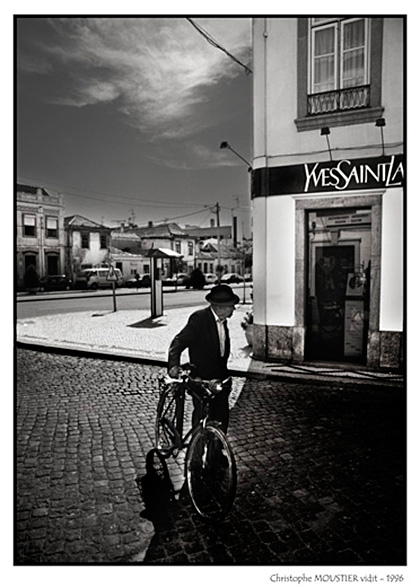
Yves Saint Laurent | la Transgression comme éthique de La Création
Logotype d’Yves Saint Laurent conçu par A.M. Cassandre. Évocation d’élégance, de créativité, de féminité; inclassable…C’est la grande patte d’un artiste complet, déjà «designer» dira Michel Disles.
Biographie d’Yves Saint Laurent
Yves Henri Donat Mathieu-Saint Laurent est né le 1er août 1936 à Oran en Algérie où il passe sa jeunesse.
En 1954, à l’âge de 18 ans, il s’installe à Paris où il suit des cours de dessin à la chambre syndicale de la haute couture pendant trois mois.
Maison Christian Dior
Christian Dior, le couturier qui a inventé le NewLook en raccourcissant les jupes des femmes d’environ 20-25cm (1945-1947)
Yves Saint Laurent est remarqué en 1955 par le couturier Christian Dior qui l’emploie comme assistant modéliste.En 1957, il est âgé de 21 ans à peine lorsque Christian Dior meurt. Il lui succède à la tête de la maison Dior où il connaît le succès avec la présentation de sa première collection  » Trapèze « . L’homme d’affaires Pierre Bergé entreprend de gérer sa carrière à partir de 1958 mais est mobilisé sous les drapeaux. À son retour, Marc Bohan a pris sa place auprès de son ami.
Vintage Fashion Newreels 1960s
Yves Saint Laurent, 1962
Yves Saint Laurent: ELLE magazine
Yves Saint Laurent, tout terriblement
L’œuvre d’Yves Saint Laurent a aussi bien sa place sur les corps au plastique parfait des femmes que dans le musée de la Mode, alors pourquoi pas sur le blog d’un graphic-designer qui pense que la création est forcément transversale et touche à tous les domaines. Je ne me suis pas privé d’évoquer le travail de Serge Lutens ou d’analyser la mise en page des magazines de Mode. Alors pourquoi devrais-je considérer qu’en la matière l’œuvre d’Yves Saint Laurent échapperait aux champs d’investigations de Design et Typo. (1) (2) (3)
Depuis la fin de la deuxième guerre mondiale les créateurs de mode se sont ouvert au monde du graphic design. Preuve en est aussi bien chez Christian Dior que Givenchy ou Ted Lapidus ou encore et bien évidemment Kenzo et Jean-Paul Gaultier sans oublier un des plus passionnés de graphisme Paul Smith. Il suffit de feuilleter les magazines sur le site de l’Officiel, pour s’en convaincre. Lignes parallèles ou croisés, trame à points façon Roy Lichtenstein. Le graphisme du Bauhaus, mais aussi la peinture cubiste de Picasso ou encore l’architecture de l’espagnol manière Gaudi ont pesé lourd sur les épaules frêles des manequins défilant d’un pas incertain sur les podiums des avant-premières.
Parce que la force créatrice des couturiers c’est aussi cela, nez au vent, sentir l’air des tendances et des désirs des femmes, traduire avant tout le monde une structure et des matières qui vont habiller les soirées mondaines et faire dire à tous ces corps, livrés aux ciseaux et points de couture, la sensualité et l’élégance du jour et de l’heure exacte, une Mode, qui arrête le Temps l’espace d’une saison.
Yves Saint Laurent a été l’un de ceux-là. Et sans doute l’un des plus brillants parce que sa sensibilité exacerbée, son exigence jamais satisfaite ont donné naissance à une représentation parfaite de l’Idéal de Mode qui ont inspiré par la suite tous les Tom Ford des générations futures.
Les pages ci-dessus et ci-dessous proviennent du site de l’Officiel de la Mode que nous avons déjà évoquées dans un billet précédent.
Les magazines de Mode ont tenté de suivre la créativité des artistes couturiers sans jamais les égaler, sauf peut-être à l’époque brillante des Harpers et de Vogue qui ont bénéficié de l’apport des Brodowitch et plus tard des Neville Brody (The Face) .
Juste un clin d’œil en montrant cette affiche du film de Robert Altman: «Prêt-à-Porter» qui brossa l’un des tableaux les plus vitriolesques du petit monde de la Mode. Un film secondaire certes mais au regard sans concession sur un système qui fait et défait le Temps de la Mode.